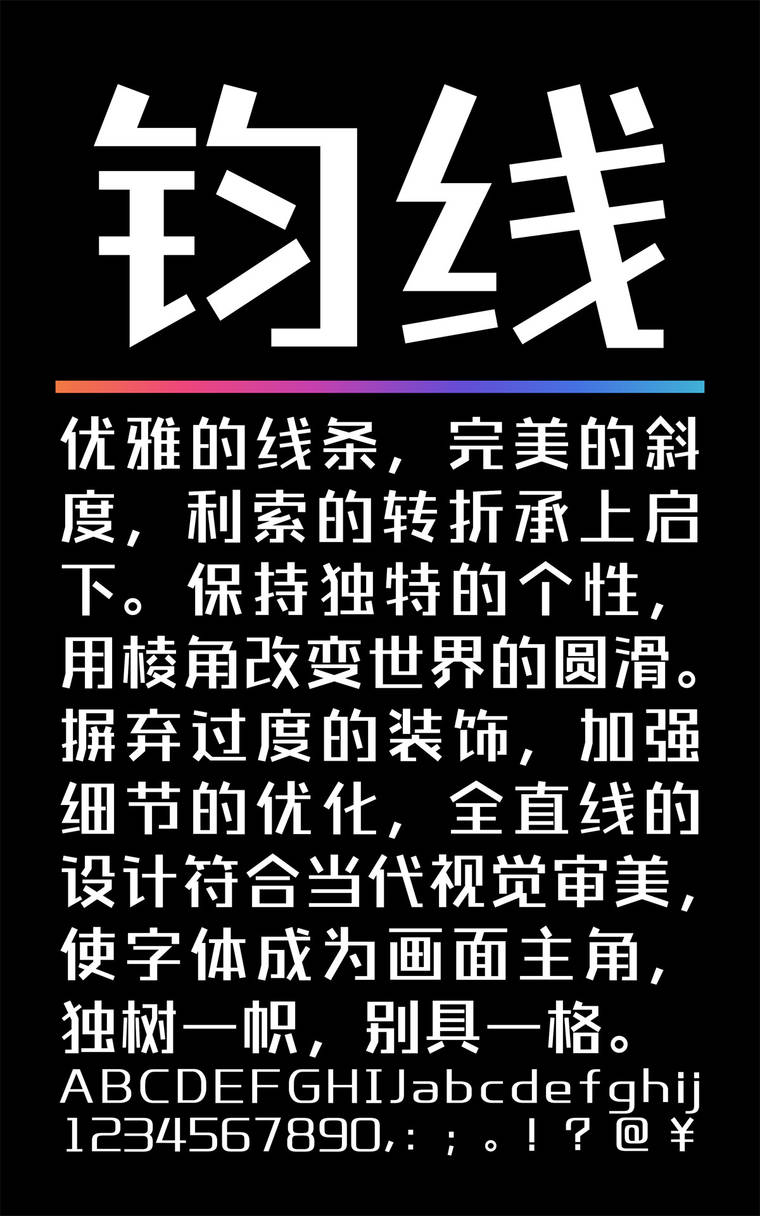
锐字钧线简 细黑
锐字钧线简 细黑字体介绍
字体特征:优雅的线条,完美的斜度,利索的转折承上启下。保持独特的个性,用棱角改变世界的圆滑。锐字钧线体,摒弃过度的装饰,加强细节的优化,在视觉上降低阅读障碍,为读者提供更加舒适的阅读体验。此外,全直线的设计符合当代视觉审美,使字体成为画面主角,独树一帜,别具一格。